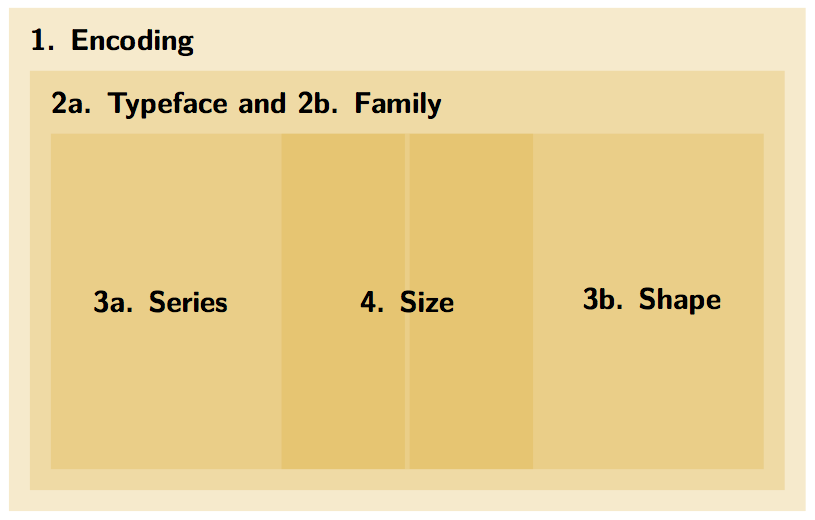
Visualisierung von Daten-Vererbung in Tabellen
wer meine zahlreiche, wirre Threads verfolgt hat, wird festgestellt haben, dass ich mich zur Zeit mit der Geometrie von Buchstabentypen auseinandersetze.
Die Idee ist eine Suchmaschine, die mir sagen kann, welche geometrischen und formalen Besonderheiten hinter den Buchstaben eines Suchworts stecken.
Ich gebe z.B. „UMT“ in die Suchmaschine ein und als Suchergebnis erhalte ich eine Auflistung an geometrischen Besonderheiten, die den Buchstaben in dem Suchwort unterliegen.
Hier ein Ausschnitt an möglichen Analysen des „UMT“:
Alle Buchstaben haben …
1. … einen Stamm
2. … eine vertikale Symmetrie
3. … keine umschlossene Fläche
Das ist nun sehr theoretisch, doch die Idee ist, dass man dieses Wissen nun für die Umsetzung eines Logos nutzen kann.
Spontanes Beispiel (gibt sicher bessere Ideen)
1. Stamm: Die Letter können untereinander angeordnet werden und die Stämme werden miteinander verbunden.
2. Vertikale Symmetrie: Symmetrische Buchstaben eignen sich besonders gut für Muster.
3. Man braucht keine Brücken für Stencils.
Gerne würde ich eure Meinung zu so einer Typo-Suchmaschine hören, allerdings kommt die eigentliche Fragestellung erst im nachfolgenden Text.
Hier ist die Visualisierung dieser Datenbank-Idee.
Bei diesem Beispiel wurden andere Suchbuchstaben eingeben. Als Ergebnis sagt die Suchmaschine, dass die Buchstaben in der Groß- und Kleinschreibweise den gleichen Skelett-Aufbau haben (sS,wW, …).
Nun, wie ihr seht wird diese Datenbank immer weiter verfeinert. Die Filtereinstellungen („Groß- und Kleinschreibweise gleich“
werden ergänzt um andere Einstellungen, z.B. „mit Bögen“).
Was mir momentan an der Tabelle nicht gefällt ist folgendes: Das Prinzip der Filter-Vererbung oder der Schnittmenge ist nicht wirklich sichtbar in der Tabelle.
Alles was nach rechts geht, baut sich auf den Filter von der linksseitigen Spalte auf. Man soll sehen: Aha, das ist eine Schnittmenge davon. Am besten wäre es, wenn ich bei der Filter-Aufzählung nicht wiederholen müsste: Es sollte klar sein, die Spalten sind eine Schnittmenge von der linken Seite.
Habt ihr Ideen, wie ich das deutlicher machen könnten?
Also erstmal finde ich die Idee irgendwie ganz witzig, auch wenn ich grad noch nicht sicher bin, ob ich sie auch praktisch finde ;-)
Rein optisch gefällt mir deine Tabelle gut, aber inhaltlich ist sie tatsächlich nicht so gut verständlich. Was hälst du davon, die Kästen jeweils ineinander einzubetten? Ich hab was ähnliches mal zur Schriftklassifizierung gemacht:
Ein anderer Gedanke: Warum ist in dem Beispiel der erste Filter „Groß/klein gleich“? Weil der die meisten Übereinstimmungen hat?
Und die Prozentwerte bzw. deren Herkunft erschließt sich mir auch nicht. Vielleicht ist aber auch das Wort „Wahrscheinlichkeit“ hier irreführend. Entweder dich Buchstaben sind in der Kategorie oder nich, oder?
Edit: Ich musste etwas überlegen, um zu verstehen, das die Schwarzen Buchstaben jeweils die anderen in der Gruppe sind und mit den Gesuchten sonst erstmal nix zu tun haben. Die würde ich gestalterisch noch weiter zurück nehmen (hellgrau z.B.)
Ah, noch etwas: „Filter“ klingt für mich nach einer aktiv durch mich getroffenen Einstellung, das ist zumindest in dem oben gezeigten Screenshot aber ja gar nicht der Fall. Insofern ist da vielleicht „Merkmal“ oder „Eigenschaft“ besser. „Kategorie“ ginge evtl. auch …
Aaah, untereinander macht’s absolut mehr Sinn. Danke Tobi!
Ja die Prozentwerte sind noch Loremipsum-Werte. Wenn man z.B. eine Kategorie hat, in der nur ein Buchstabe vorkommt und man eben diesen entsprechenden Buchstaben sucht, dann sagt die Datenbank: Wahrscheinlichkeit = 3,8%  (1/26). Der Designer weiß dann, dass dieser Buchstabe in dieser Hinsicht etwas Besonderes ist und kann diese Besonderheit in der Gestaltung herausstellen.
Dem Kunden könnte man dann sagen, dass diese Umsetzung nur mit diesem einen Buchstaben möglich ist. Man hätte dann ein Logo, dass sehr originell ist bzw. ein Alleinstellungsmerkmal hat.
Freut mich, dass du vor das Wort Spielerei „spannend“ gesetzt hast!
So eine Mechanik kann wirklich eine spannende Spielerei sein, das mein ich schon ernst. Aber es wird halt nicht mehr als eine Spielerei sein.